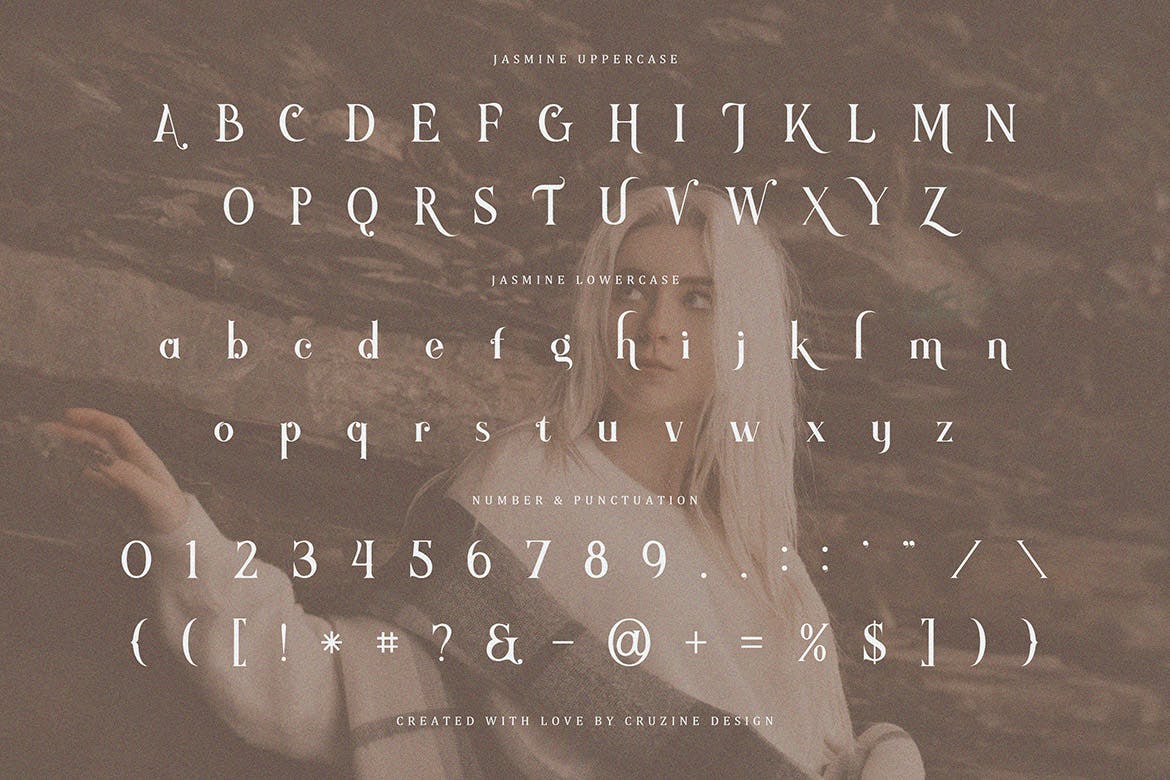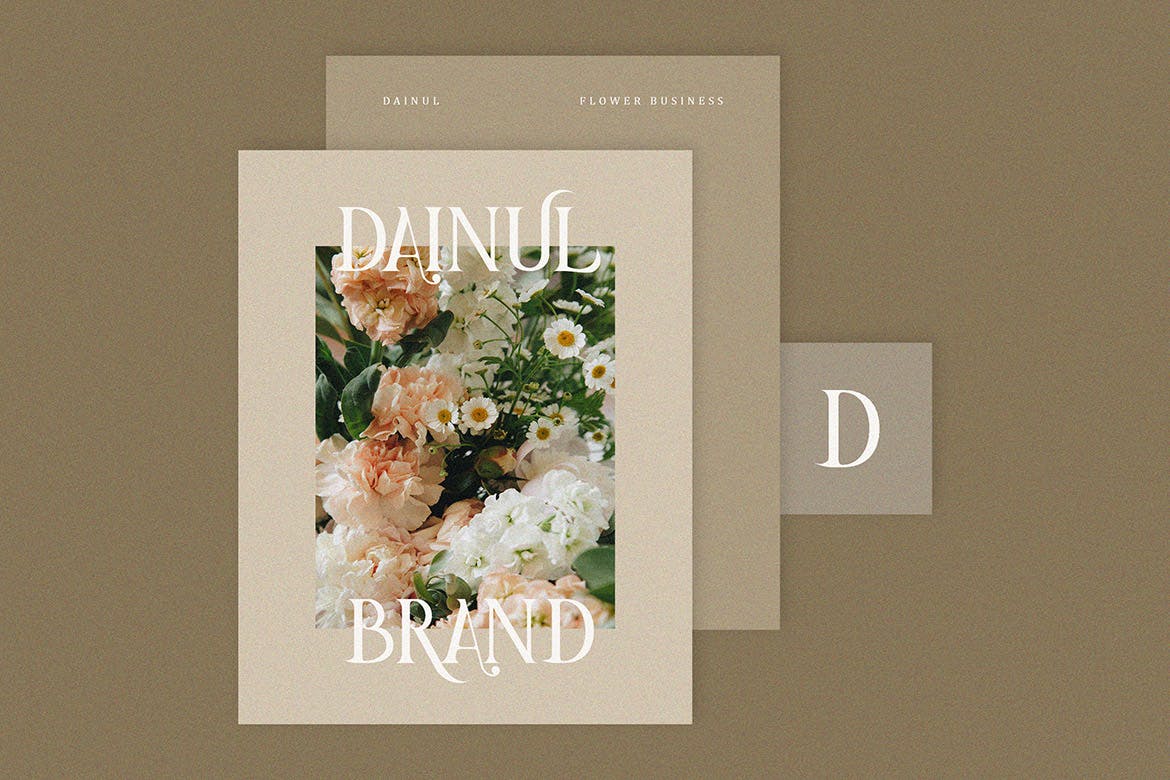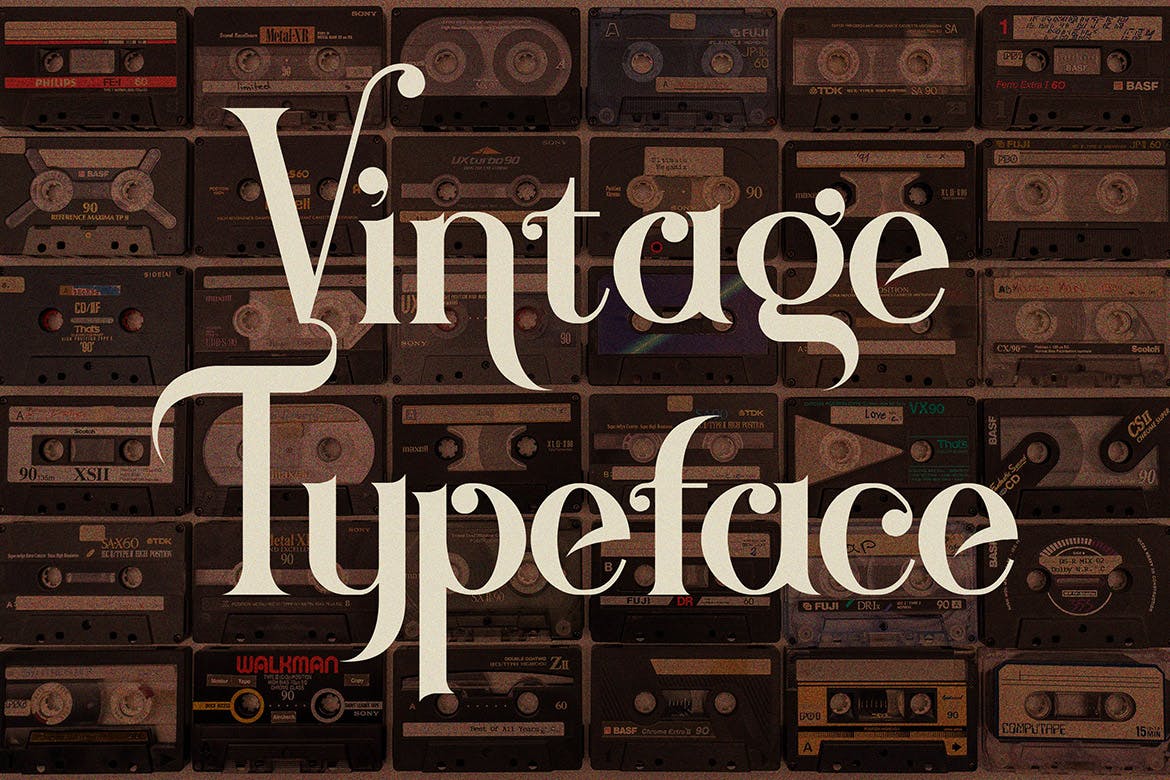
Jasmine Vintage Font
فونت جاستین وینتج، ایده‌آل برای پروژه‌های طراحی کلاسیک و دکوری.
فونت جاستین وینتج، یک فونت وینتج، دکوری، رترو و با طراحی کلاسیک است. این فونت برای لوگوها و پروژه‌های برندینگ جدید شما بسیار مناسب است.
• عالی برای پروژه‌های برندینگ با سبک رترو یا وینتج